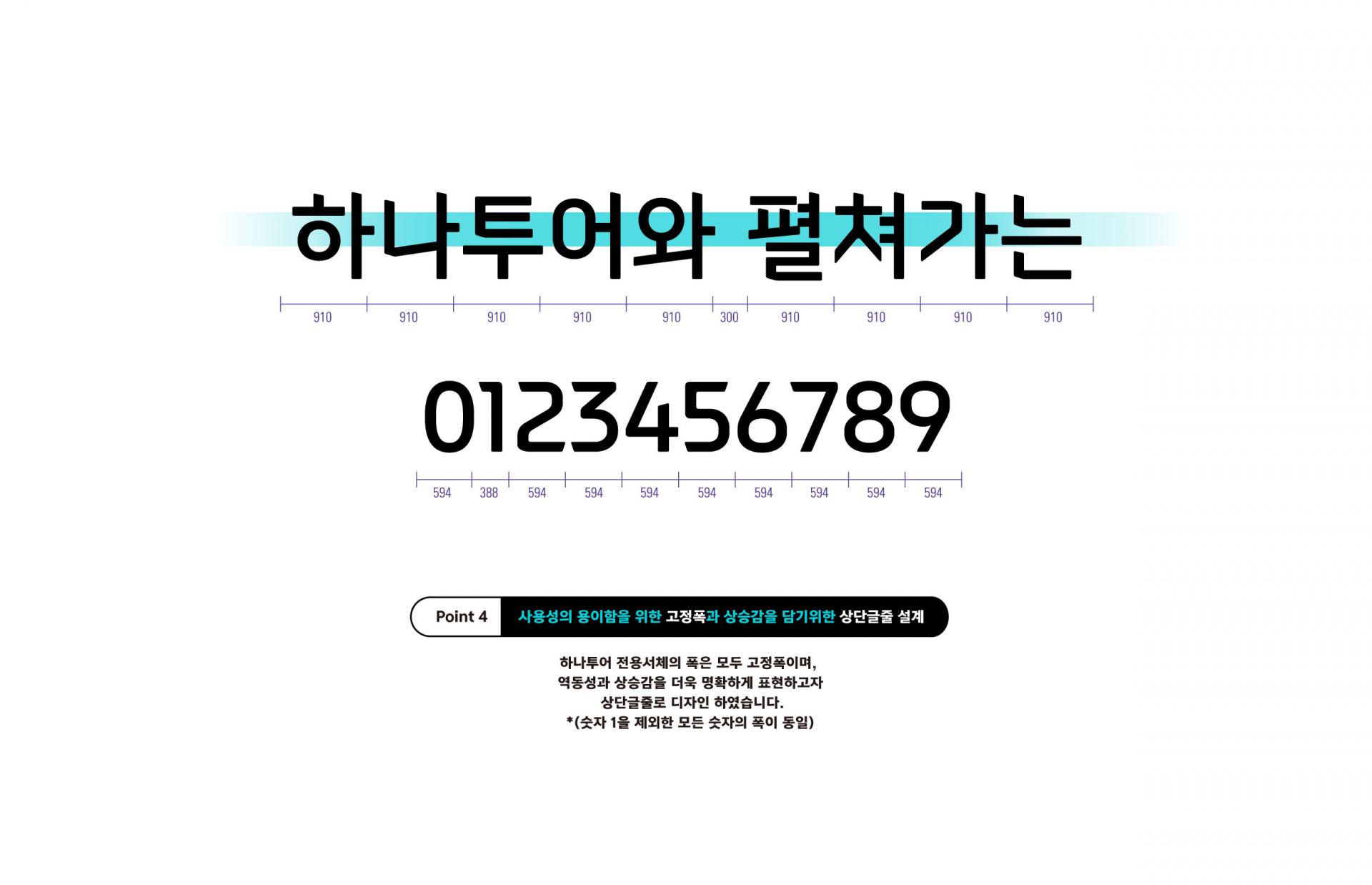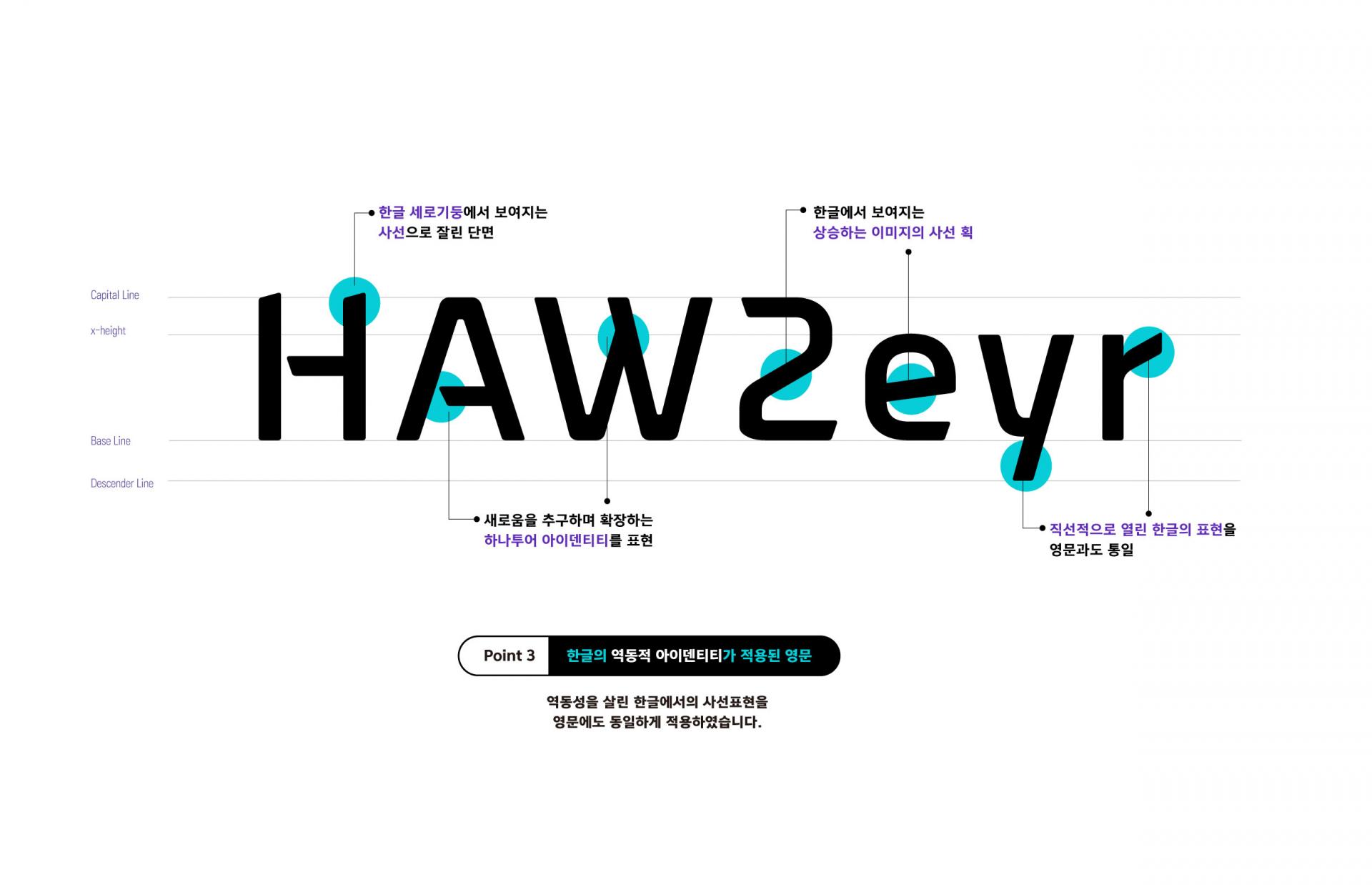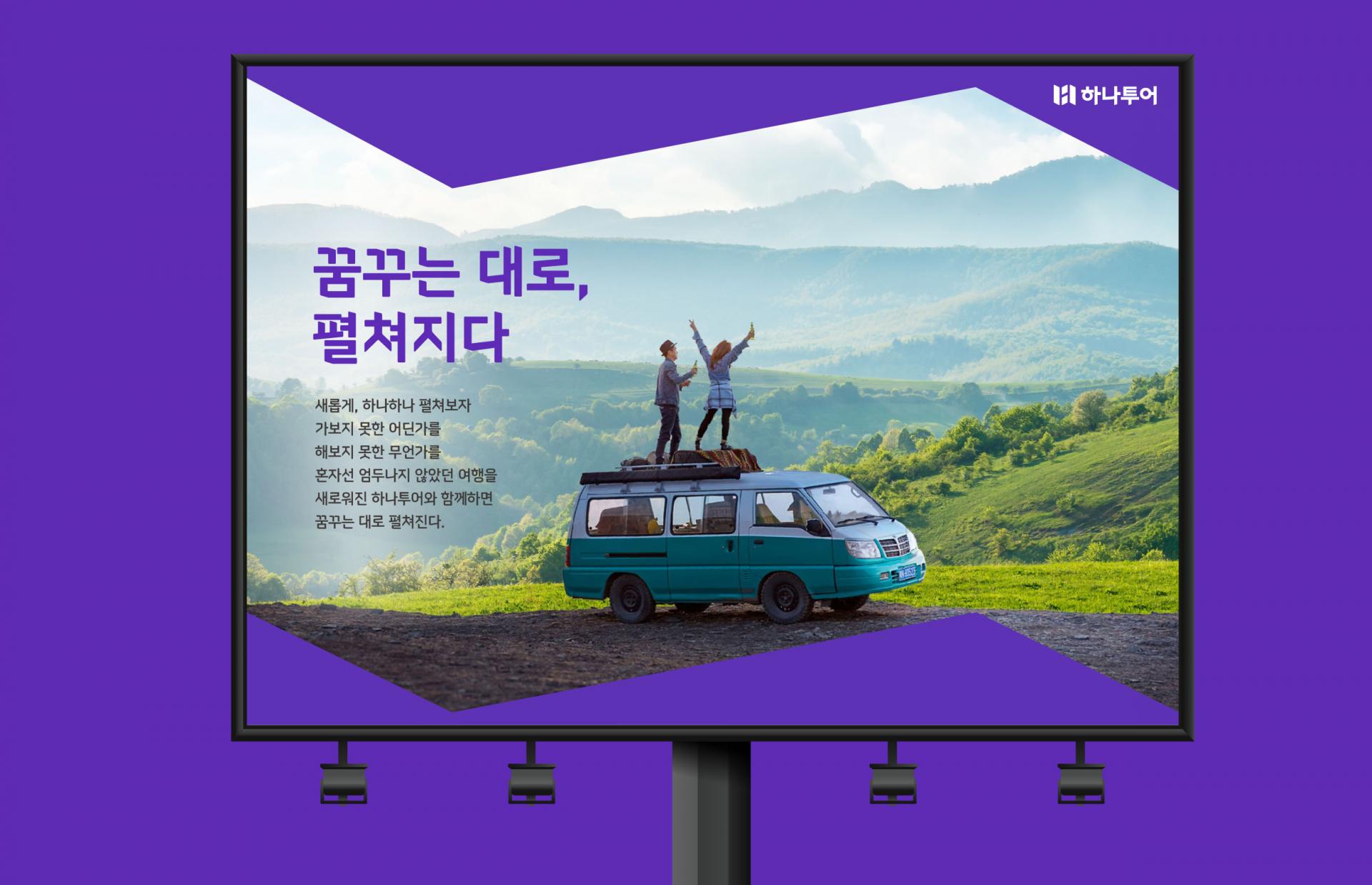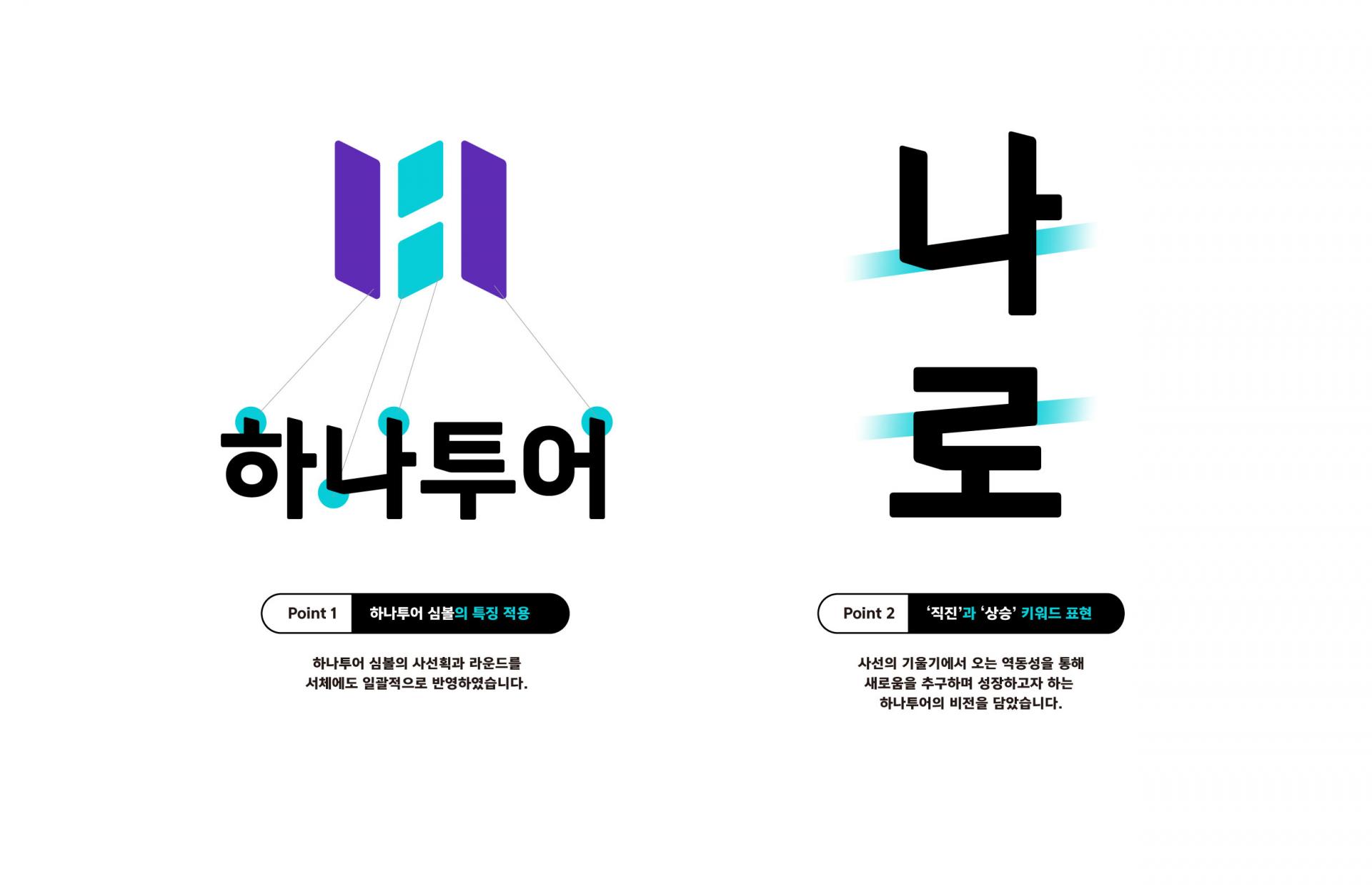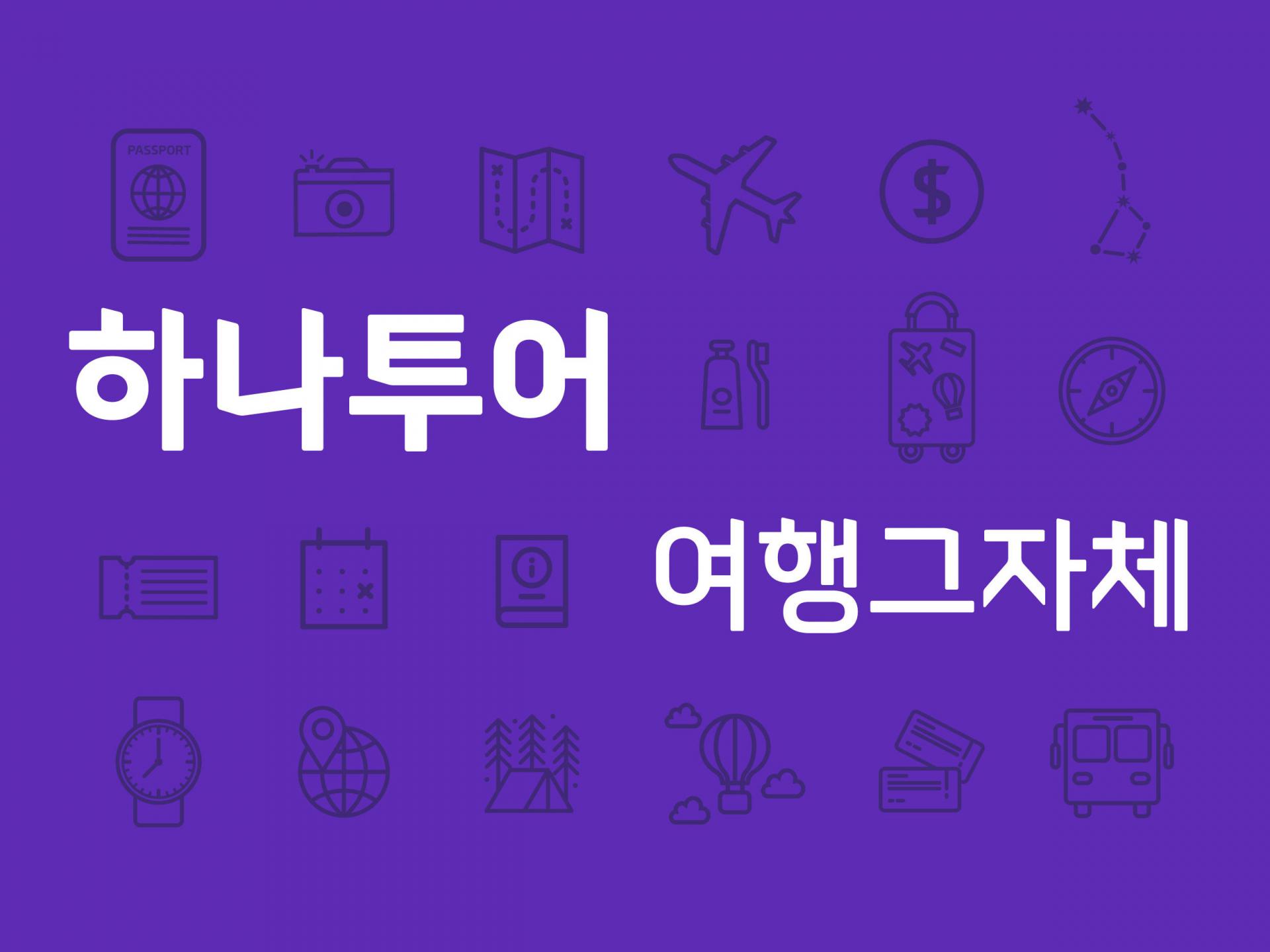
하나투어 [여행그자체]
하나투어 여행그자체는 '새로운 경험과 가능성'이라는 의미가 담긴 리뉴얼된 BI를 그래픽 모티프로 삼아, BI의 형태적인 특징과 컨셉을 담았다. '직진' '상승'을 키워드로 기울기에서 오는 역동성과 확장을 표현했으며, 새로움을 추구하는 하나투어의 비전을 담고 있다.
하나투어